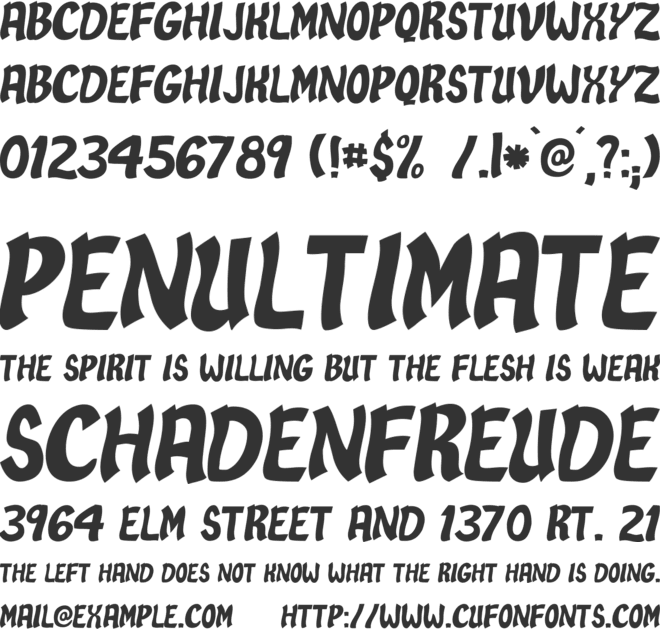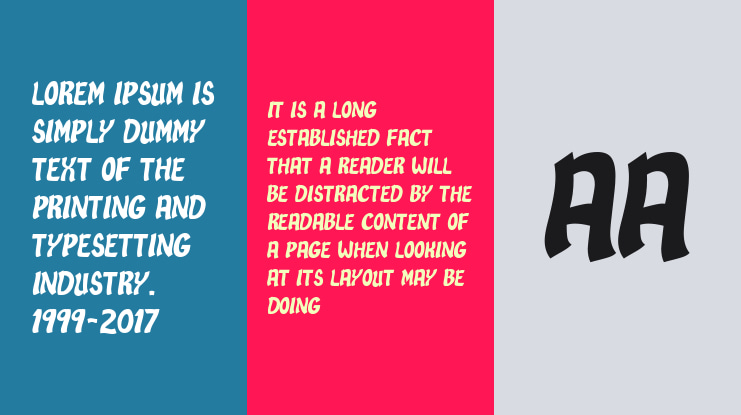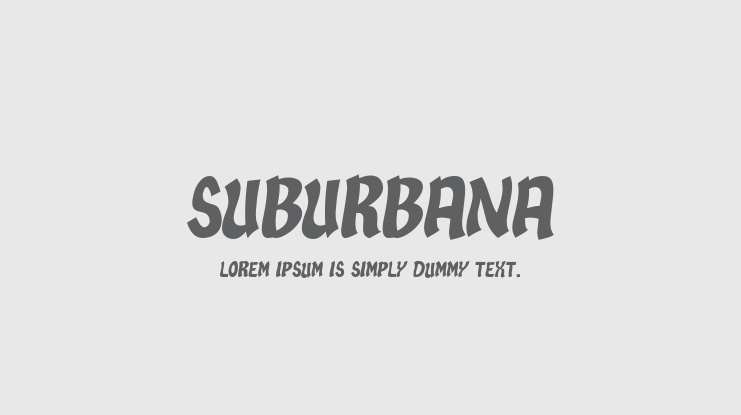
Suburbana Font
Fernando PJ
Suburbana é uma tipografia brasileira, criada pelo designer gráfico Fernando PJ no ano de 2003, inspirado no trabalhos dos pintores de letras populares na cidade de Salvador (Bahia, Brasil). O uso é 100% gratuito, é apenas solicitado que coloque os créditos.
Suburbana is a Brazilian typography, created by graphic designer Fernando PJ in 2003, inspired by the work of the popular letters painters in the city of Salvador (Bahia, Brazil). The use is 100% free, it is only required to put the credits.
Suburbana font preview